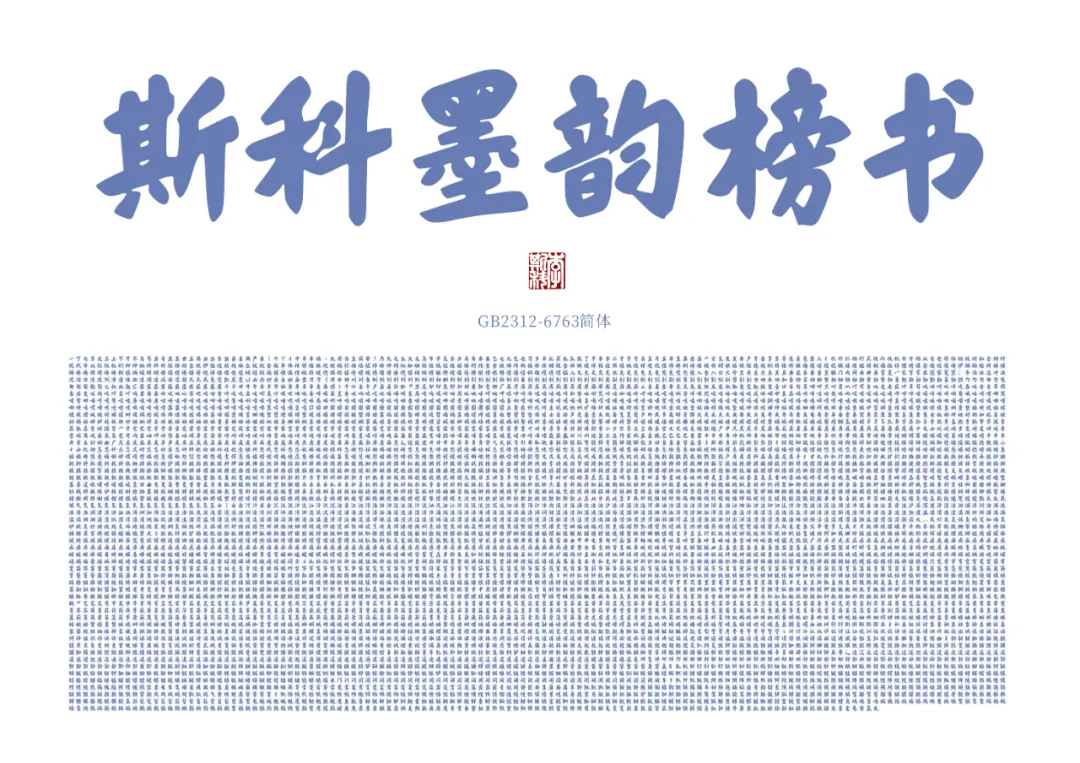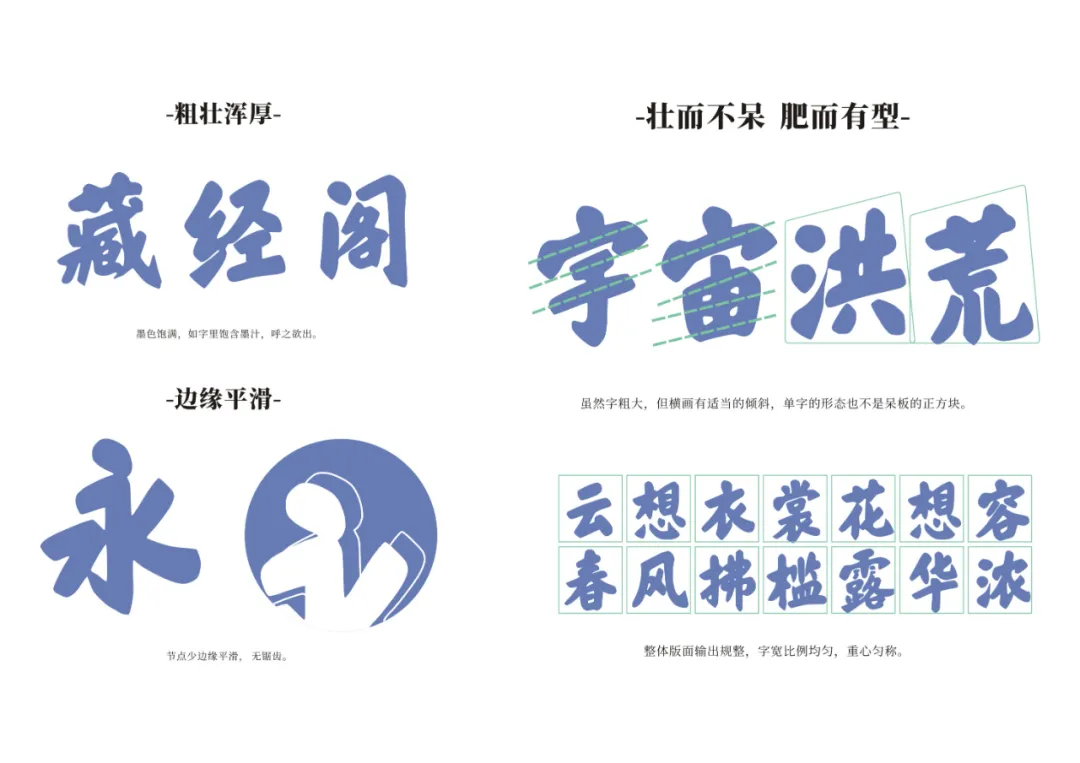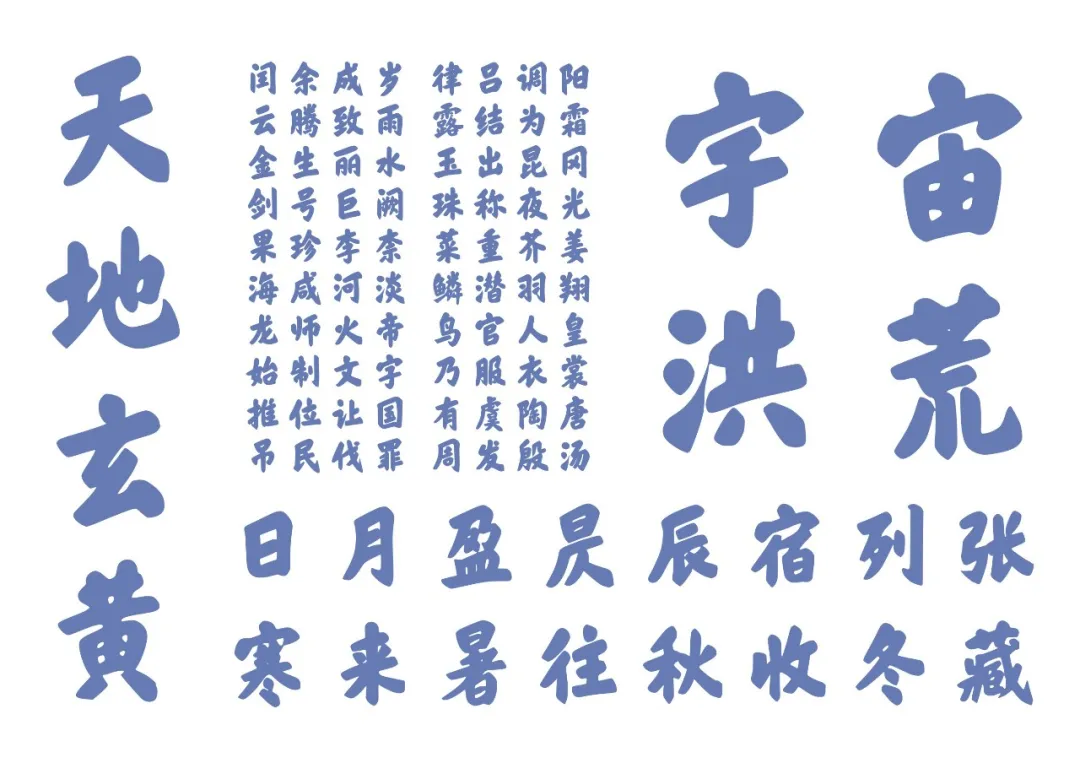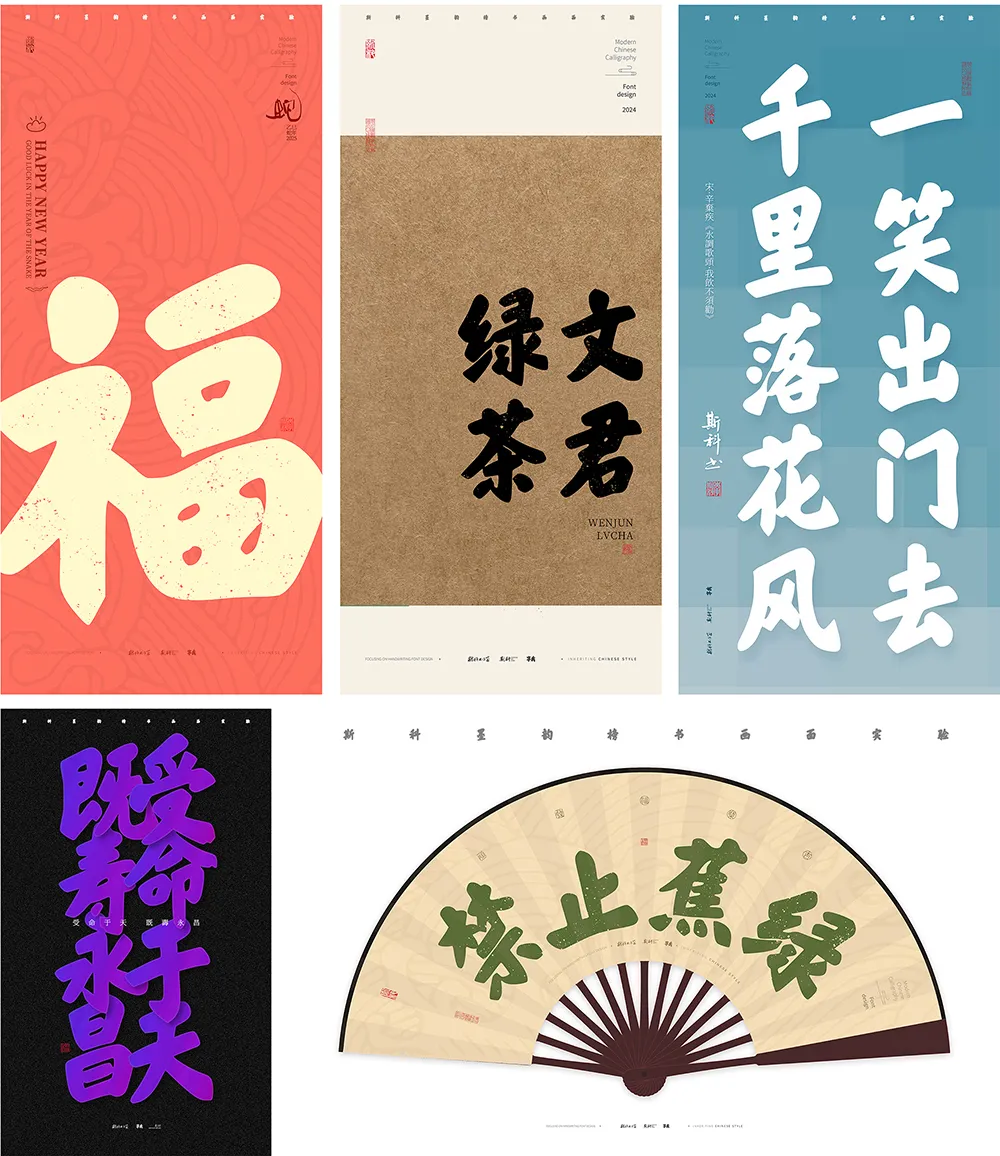
斯科墨韵榜书,字型粗壮浑厚,但又不失文雅,适用于标题、海报、招牌、包装、综艺影视、广告设计等不同场景。GB2312 编码/6763字,满足广大字体用户简体字应用需求。
这几天对『斯科墨韵榜书』做了一下升级,增加了三个之前缺失的常用字、阿拉伯数字、一些常用标点符号、英文字母大小写。有需要的朋友可以开始下载啦!(2.0版本的下载链接在本文底部)